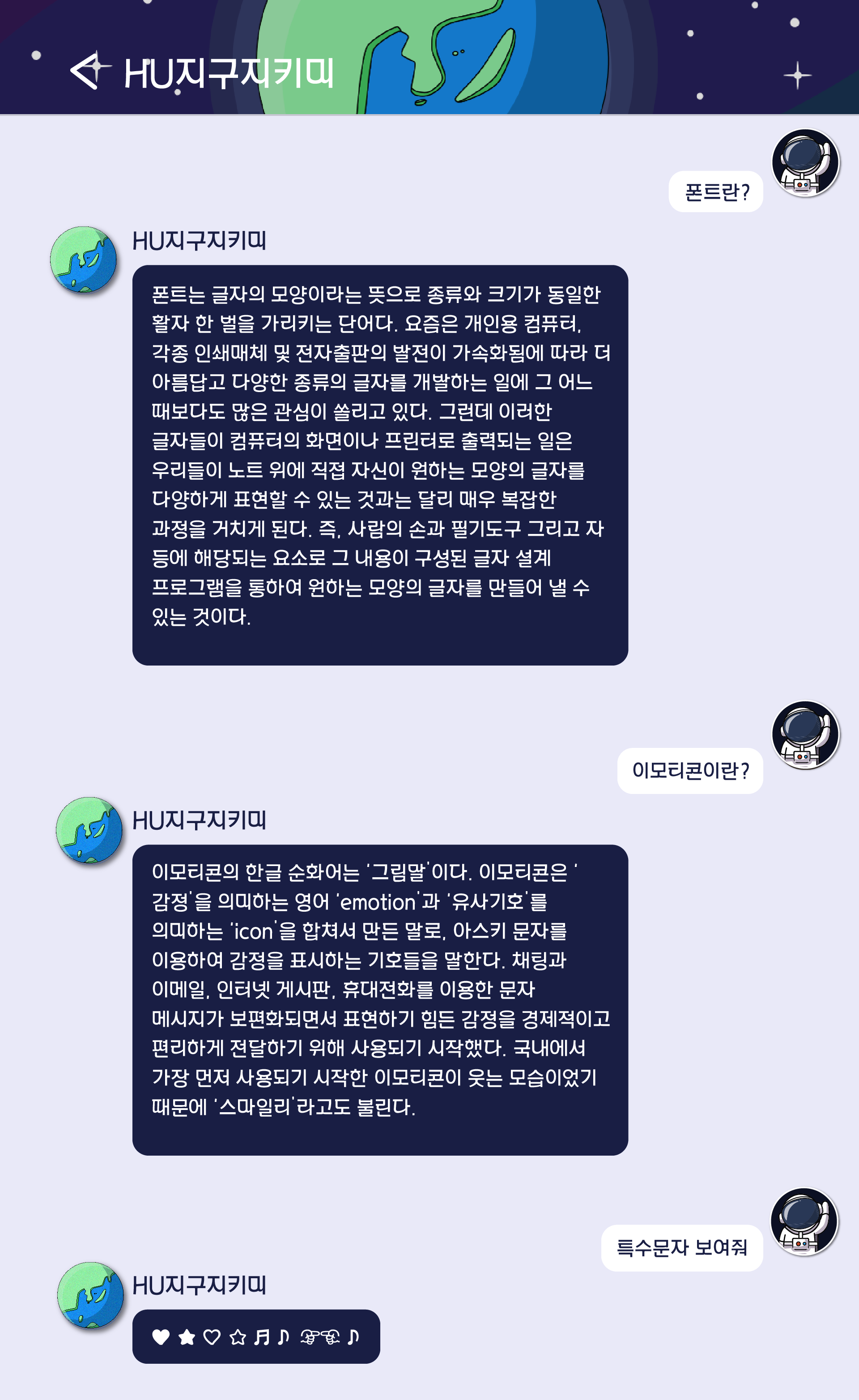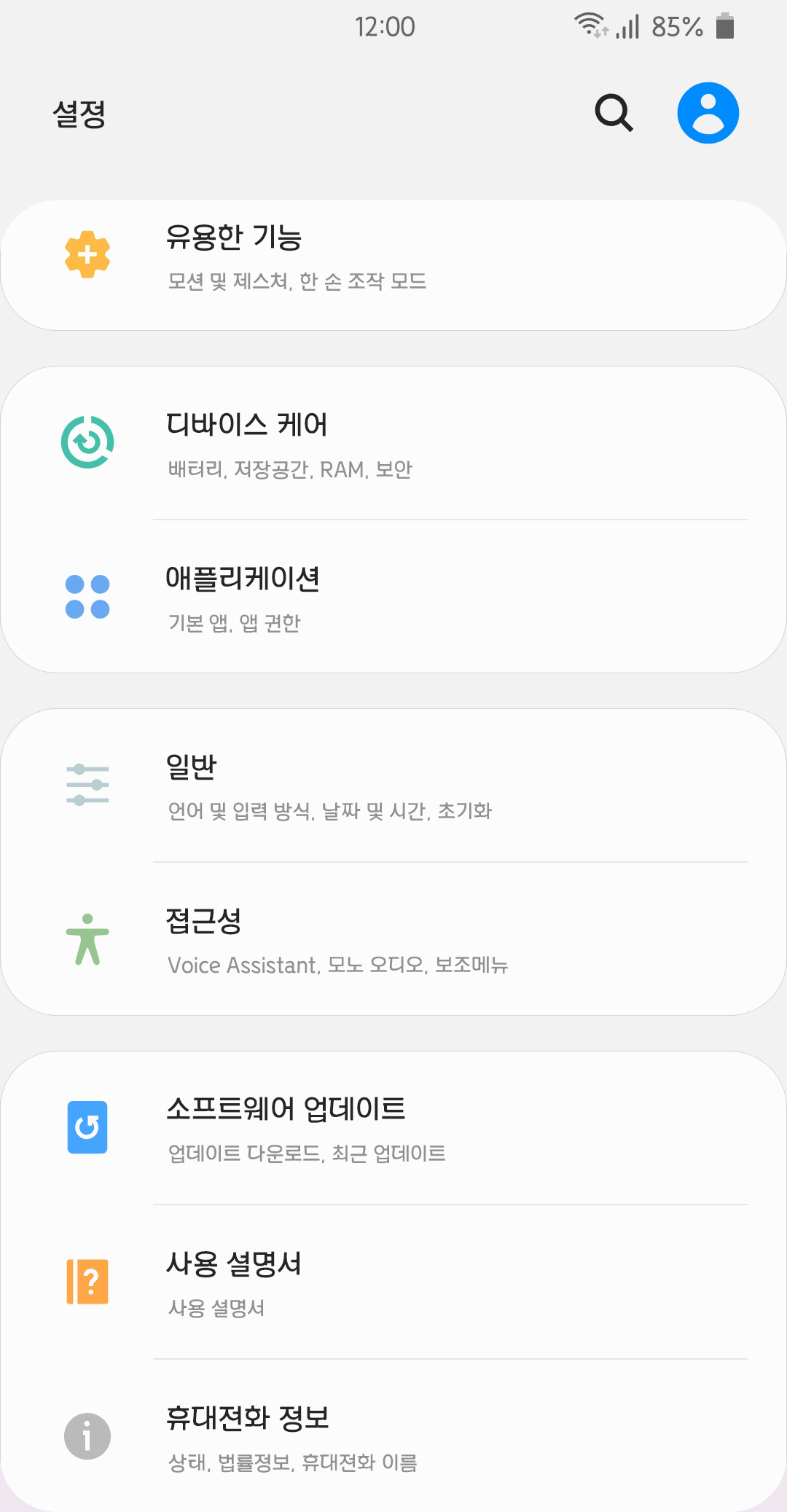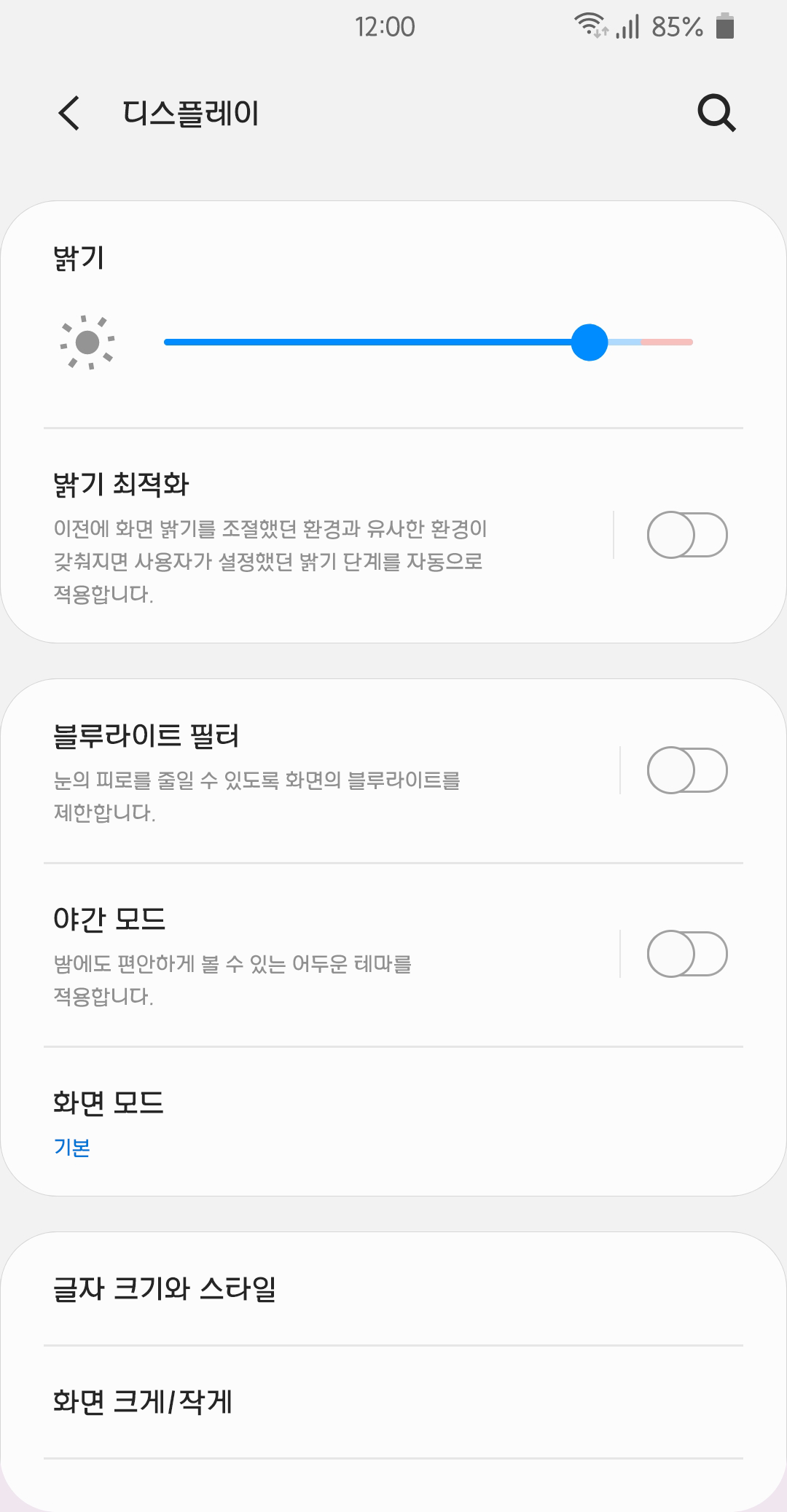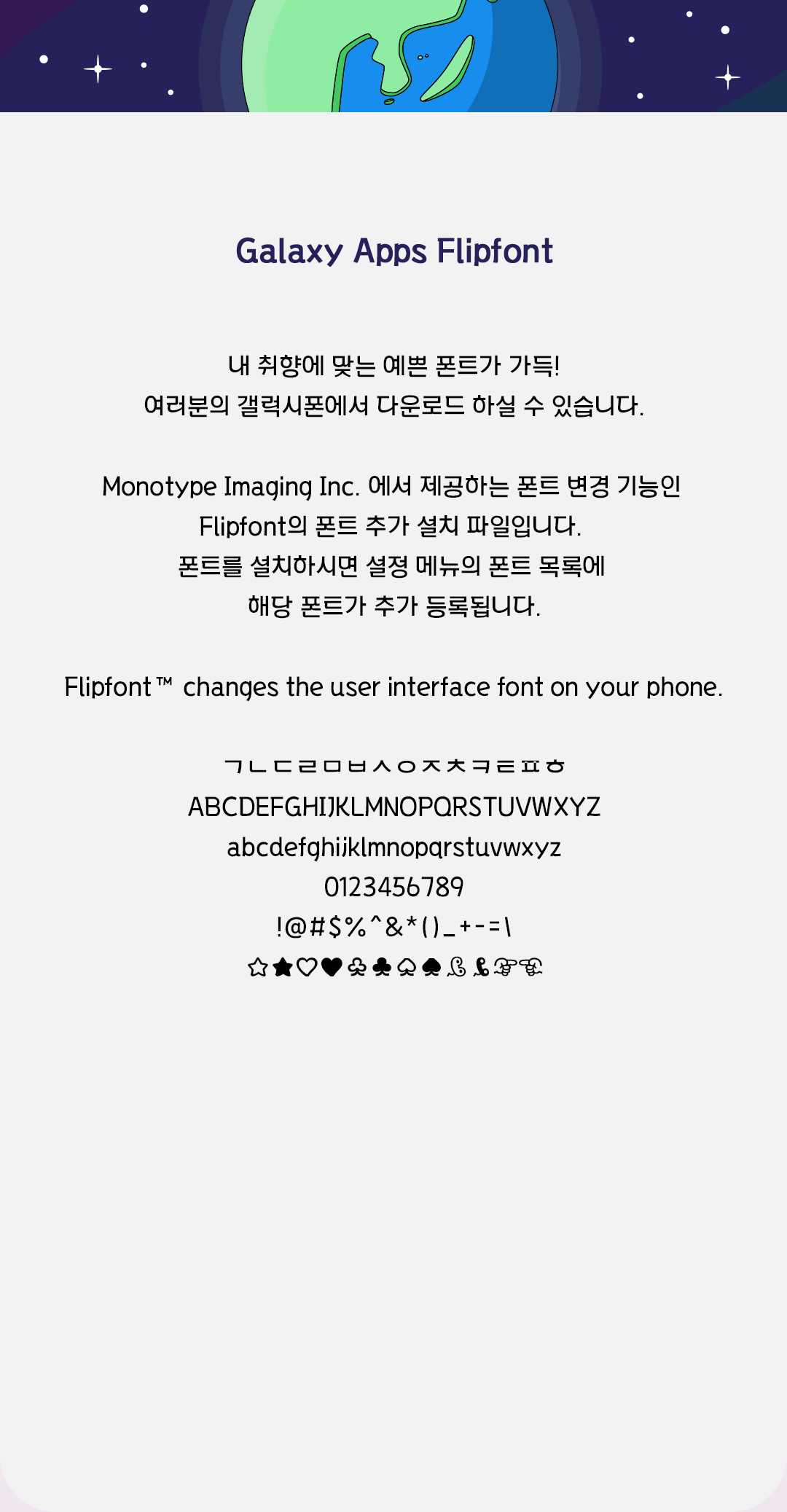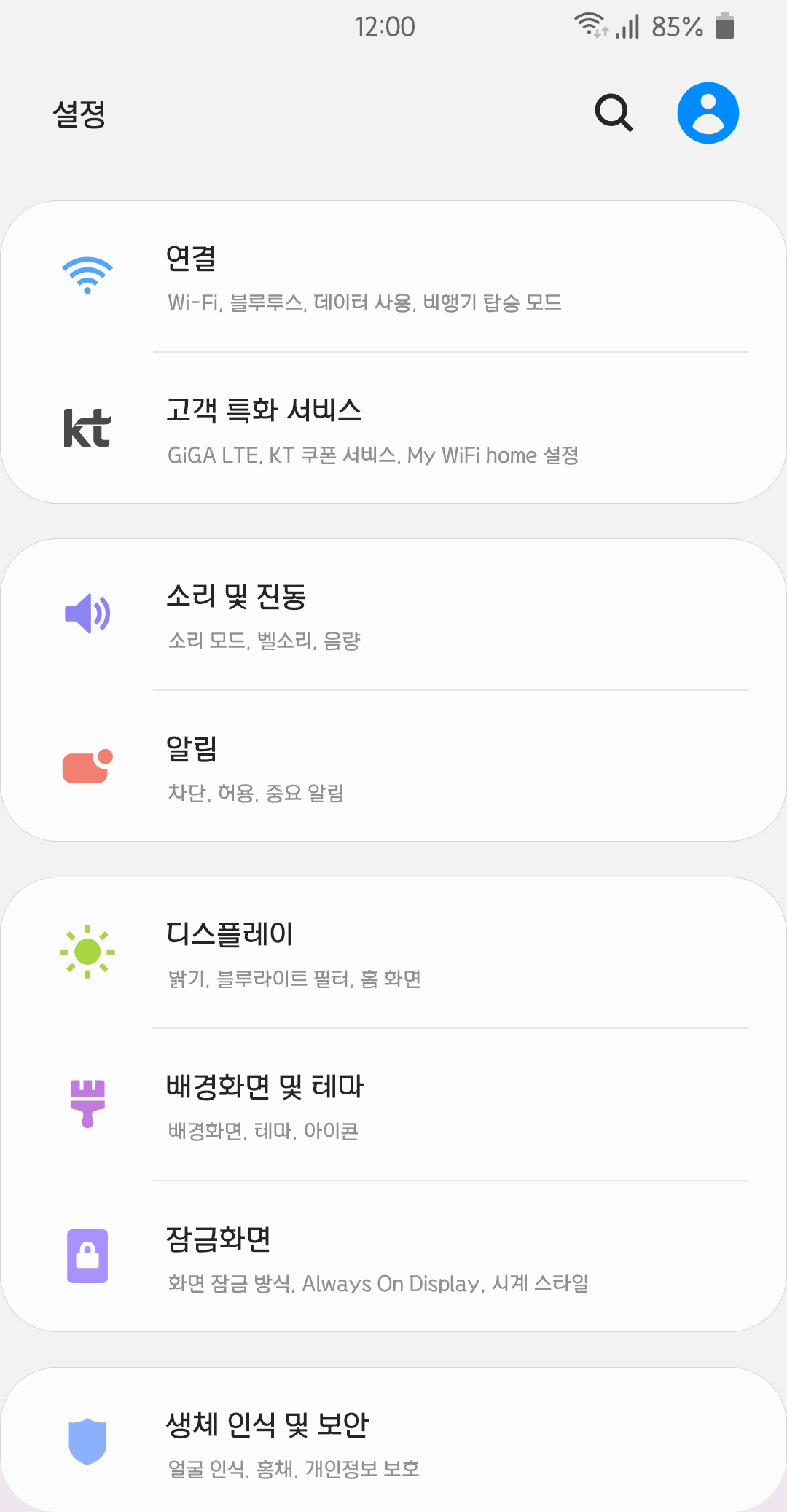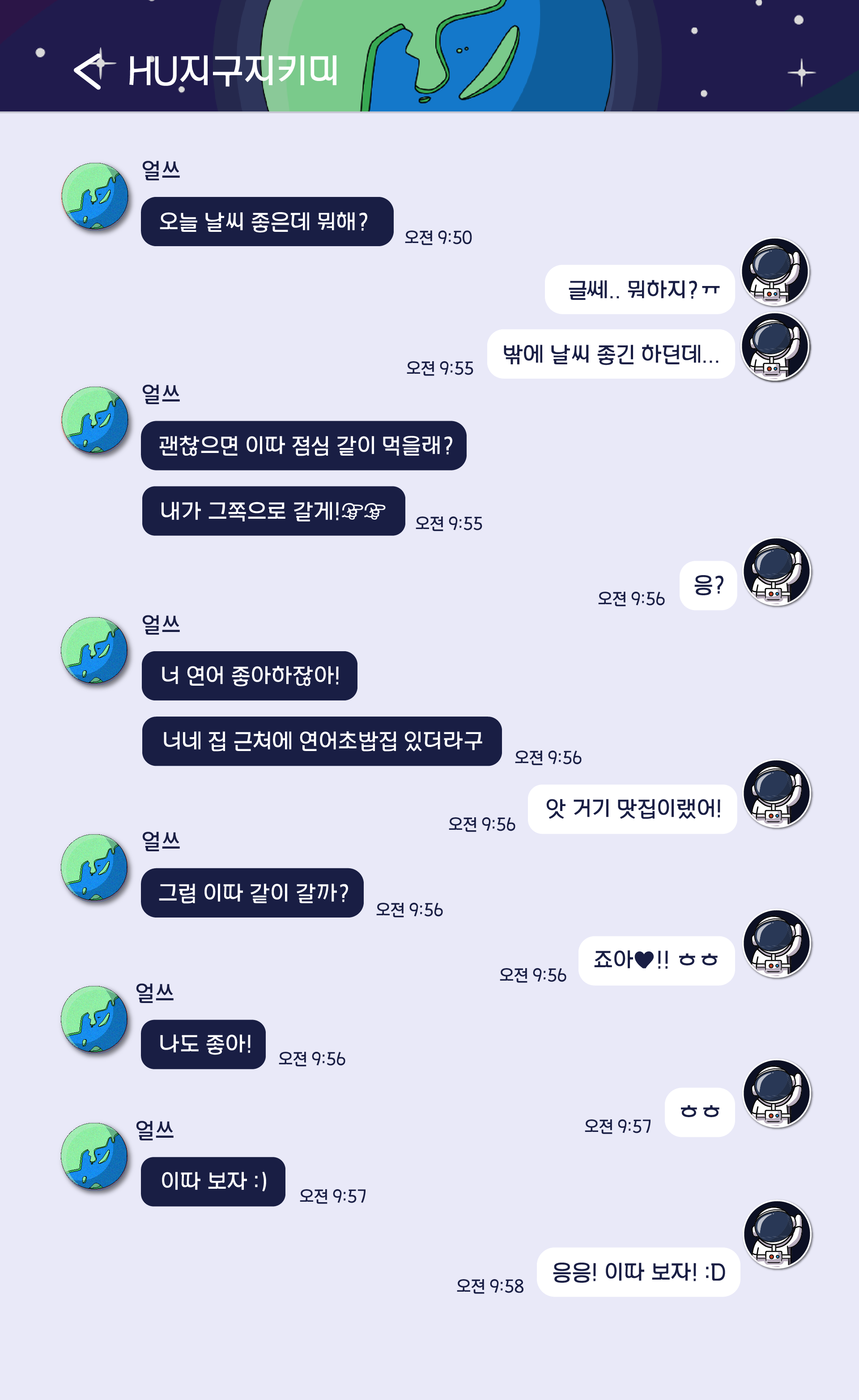
#헤드라인HU지구지키미
슈퍼히어로의 망토자락처럼 초성의 마지막 획이 모음과 이어지는 형태가 특징인 개성있는 제목용 서체입니다.
자음 ㅁ,ㅂ,ㅍ과 모음ㅗ의 형태가 ㅅ 느낌으로 제작되어 귀여움을 살렸고,
위쪽 정렬되어 글자 높낮이에 따른 리듬감이 느껴지는 헤드라인 서체입니다